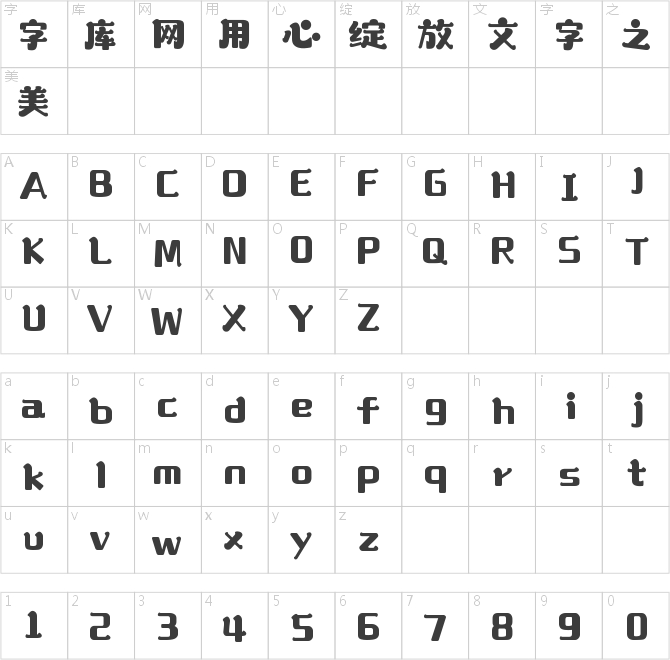
山海小龍貓,是一款卡通風字體,包含簡體漢字6763個。字體童趣可愛,結構多變靈動,字形活潑清新,造型生動有趣,具有靈活的適用性,天真俏皮又不失時尚感。
山海小龍貓字體字庫是一款讓人賞心悅目、百看不厭的中文字體,適合各類廣告和產品包裝設計應用,字體大小3.25MB,格式為ttf字體,上傳用戶是山海字庫,作者/版權方為山海字庫